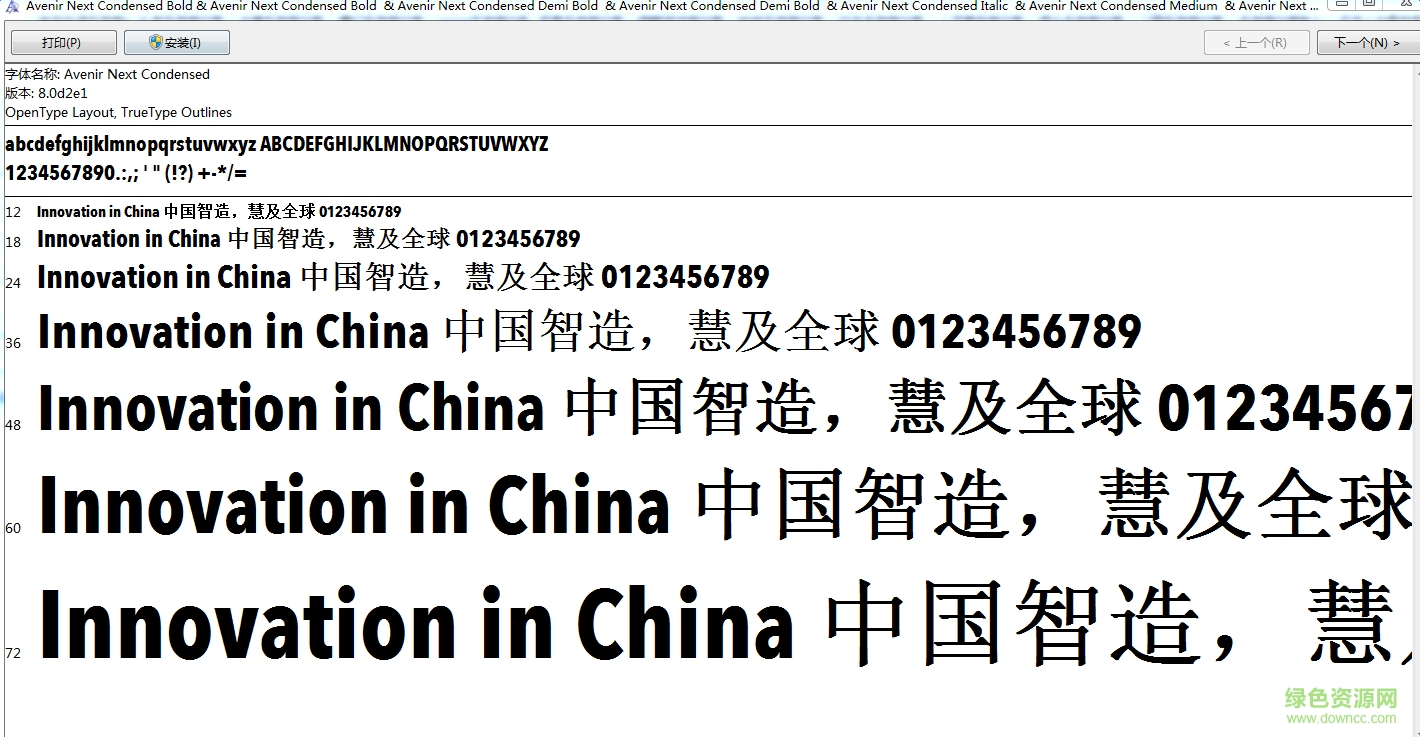
avenir next condensed regular字體
avenir next condensed字體是一款英文字體,字形端正,字體粗黑,筆墨勻稱,整體布局嚴(yán)謹(jǐn)縝密,感興趣的朋友快來綠色資源網(wǎng)下載吧!
avenir next condensed字體規(guī)矩整齊,工整端正,字體間距剛剛好,閱讀體驗(yàn)極佳,可應(yīng)用的領(lǐng)域也十分廣泛!